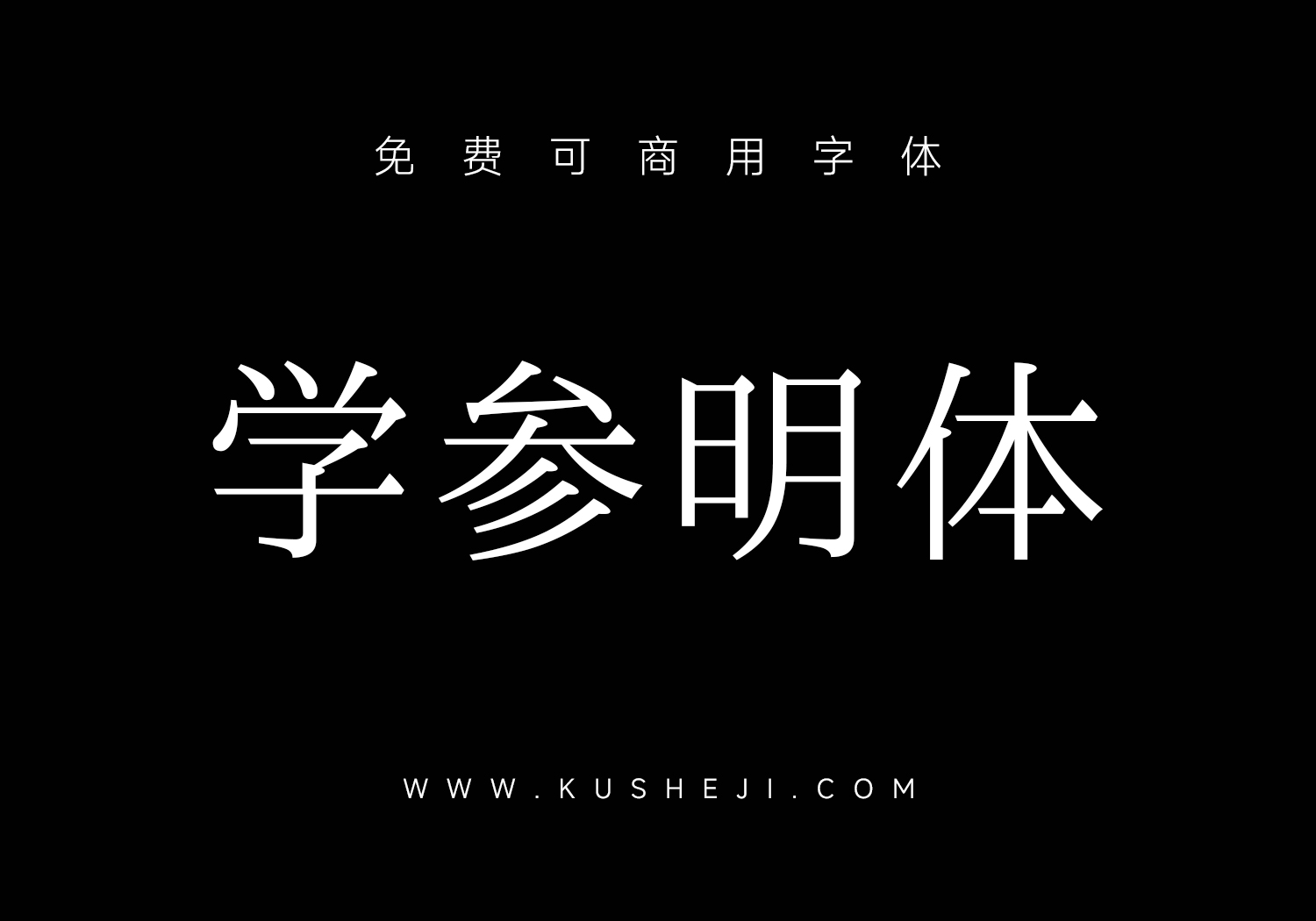
因漢字字形之硏究所需,目前沒有符合硏究需求的字型可用,故啟動本計劃,製作符合需求之字型。目前的字型成品有:
Study Ming JP(学参明朝体 日本 印刷):
主要依《常用漢字表》(東京:文化庁,2010年),以及《常用漢字表の字体・字形に関する指針(報告)》(東京:文化庁,2016年)中的明朝體字形,檢校、修改當中常用字的漢字字形。
Study Ming JA(学参明朝体 日本 教科書):
主要依《常用漢字表の字体・字形に関する指針(報告)》(東京:文化庁,2016年)中的教科書體字形﹐並參考表中的手書文字例子字形,以及モトヤ、モリサワ、イワタ等字型廠商的学参明朝体,檢校、修改當中常用字的漢字字形。
Study Ming HK(學參明體 香港):
主要依《常用字字形表》(香港:香港特別行政區政府敎育局課程發展處中國語文敎育組,2012年)及《香港小學學習字詞表》(香港:香港特別行政區政府敎育局課程發展處中國語文敎育組,2007年),並參考《常用字字形表(二零零年修訂本)》(香港:香港敎育學院,2000年)和《香港電腦漢字參考字形》(香港:香港特別行政區政府政府資訊科技總監辦公室、公務員事務局法定語文事務部,2017年),檢校、修改當中常用字的漢字字形。
Study Ming TW(學參明體 臺灣):
主要依《國字標準字體宋體母稿〈敎育部字序〉》(臺北:敎育部國語推行委員會,1998年),並參考《國字標準字體楷書母稿〈敎育部字序〉》(臺北:敎育部國語推行委員會,1998年)、《常用國字標準字體表》(臺北:敎育部,1982年),檢校、修改當中常用字的漢字字形。
Study Ming CN(学参明体 中国):
主要依《通用規範漢字表》(北京:敎育部、國家語言文字工作委員會,2013年),檢校、修改當中常用字的漢字字形。
爲方便不同語系的作業系統使用,避免在其他語系的作業系統或軟件中失效,這些字型的實際名字都只有英文名。所有字型的字高、行高皆與一點字坊的新一細明體統一,除了可以與之搭配使用,亦能與視窗作業系統預設的「細明體」搭配,不會出現行高改變之問題。